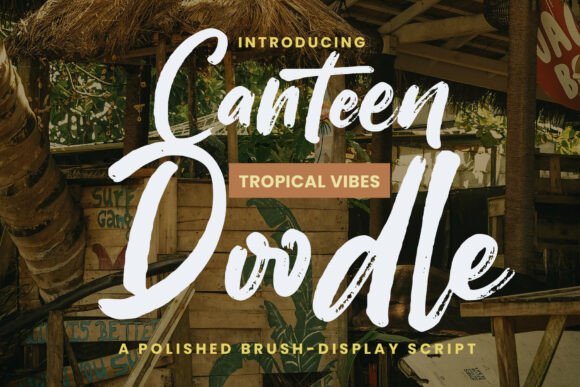
Canteen Doodle
適切なデザイン要素を見つけるのは難しい場合がありますが、Canteen Doodleは作品を即座に引き立てる優れたコレクションを提供します。
POD(オンデマンド印刷)製品、結婚式の招待状、またはソーシャルメディアのグラフィックを作成している場合でも、Canteen Doodleは理想的です。